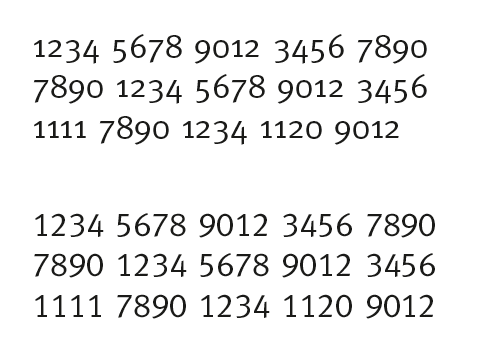
Corporate Design: Zahlen strukturieren
Ich befasse mich gerade mit einem unserer Lieblingsthemen: dem Strukturieren von Zahlen auf Briefbögen und Visitenkarten. Zum einen ist die Sache mit der Ergänzung von IBAN und BIC ja nicht gerade leichter geworden, zum anderen gibt es schriftspezifische Dinge, über die ich gerade bei der Gestaltung stolpere.
Im konkreten Fall arbeite ich mit der Meta und habe dabei für verschiedene Drucksachen die Mediävalziffern in Gebrauch.
Bei Briefbogen und Visitenkarten, die jetzt neu gesetzt werden sollen, tue ich mich damit aber schwer, weil die langen Zahlenreihen in den Bankverbindungen (es sind tatsächlich mehrere, was die Sache nicht gerade leichter macht) einen unruhigen Eindruck erzeugen und schwer zu erfassen sind – speziell dann, wenn die Zahlen ungegliedert gesetzt werden. Meine Präferenz ist daher im Moment, für die Adressblöcke komplett auf normale oder Tabellenziffern zu setzen und darüber hinaus die IBAN-Zahlenreihen in Vierergruppen zu gliedern.
Meine Frage an Euch: Wie geht Ihr mit Mediävalziffern in Adressblöcken um? Schätzt Ihr sie wegen ihrer visuellen Anpassungsfähigkeit oder fallen sie gerade deswegen für Euch sowieso raus?
Meistens tanzen sie mir dann doch zu stark ... und die "Korrektur" des Kunden, dass "alle Zahlen verrutscht sind" kommt da garantiert ...
Somit habe ich es aufgegeben, Mediäval-Ziffern für solche Sachen einsetzen zu wollen, und setze pragmatisch Versalziffern, aber ich versuche sie besser zu integrieren:
• In den seltenen Fällen dass eine Schrift Petit-Caps und dann auch noch Petit-Caps-Ziffern besitzt ... bestens!
• Alternativ kommen wenn verfügbar Kapitälchenziffern zum Einsatz
• Wenn beides nicht da ist, und die Versalziffern zu groß wirken (VERSALSCHREIBWEISE) dann versuche ich sie 1-2pt zu verkleinern und ggf. mit der nächsten Strichstärke auszugleichen. Das ist dann Handarbeit ...
• Wenn die Zeilenabstände dann noch ungleich wirken, weil andere Zeilen in Minuskeln gesetzt sind, gleiche ich diese manuell aus.
• wenn Diktengleichheit nicht erforderlich ist (meistens nicht) verwende auch keine Tabellenziffern, oder lasse sie mittels Indesign-"optisch" ausgleichen und justiere dann noch nach.
Ich würde das genau so machen wie du beschrieben hast: Mediävalziffern im Fließtext, Tabellenziffern für die Adressblöcke. Tabellenziffern eignen sich gerade bei mehrzeiligen Blöcken …
nur eine terminologische anmerkung: mediävalziffern und tabellenziffern sind keine begrifflichen gegensätze. man könnte deine empfehlung dahingehend missverstehen. es gibt allerdings in vielen schriftarten auch mediävale tabellenziffern und natürlich proportional zugerichtete versalziffern. falls jemand auf dieses thema stößt und noch mal wissen will, wie es ist:
zifferngestaltung:
mediävalziffern: teilweise hängende ziffern
versalziffern: nur ›stehende‹ ziffern
ziffernzurichtung:
proportional zugerichtete ziffern: jede ziffer hat ihre eigene, ›natürliche‹ breite
tabellarisch zugerichtete ziffern: alle ziffern haben dieselbe breite
wenn deine version der meta auch dicktengleiche minuskelziffern hat würde ich auf jeden fall probieren ob’s gut aussieht. aber sebastians kunden-erfahrung kennen wir natürlich alle.
Ich denke, ich zeige dem Kunden beide Varianten, da sie beide etwas für sich haben. Der Kunde ist in Gestaltungsfragen versiert, daher – denke ich – kann ich ihm die Entscheidung zumuten.  ;-)
Ich habe letzte Woche im Rahmen eines Uniseminars am Rand meines Vortrags verschiedene Schriften gezeigt, einfach um die Studierenden dafür zu sensibilisieren, dass es mehr gibt als das, was auf ihren Computern vorinstalliert ist. Es lief alles wie erwartet, bis zu einer Tafel mit Beispielen von Serifenschriften, darunter Times New Roman (quasi als Ausgangsbasis, da sie für studentische Arbeiten immer noch oft vorgegeben ist) und dann verschiedene Schriften, die ich so herum zu liegen hatte, z.B. eine Garamond, Vollkorn und die neue Kefa II. Ohne dass ich danach gefragt hätte, gab es mehrere spontane Zwischenrufe:
Student 1: “The first one [TNR] is the best!”
S2: “Yeah, it’s the prettiest.”
Ich: “Why do you prefer this typeface?”
S3: “It doesn’t have those crazy numbers!”
S4: “Yeah, those are weird!”
Darauf gab es zustimmendes Gemurmel und die ganze Klasse hat mich mit freudiger Zuversicht angestrahlt, weil sich alle sicher waren, »richtig« getippt zu haben. Beim Gestalten der Tafel war mir gar nicht aufgefallen, dass das TNR-Beispiel das einzige mit Versalziffern war. Alle anderen Beispiele hatten Mediävalziffern.
Außerdem sind Mediävalziffern je nach Schriftart ganz anders ausgeprägt. Bei manchen Schriften sind die Ober- und Unterlängen im Vergleich zum Rest besonders groß, bei anderen Schriften besonders klein. Ist letzteres der Fall, kann man die Ziffern viel eher auch wie Versalziffern benutzen. Kommt immer drauf an. Und wann man zwei Ziffernarten in einer Drucksache oder einem Corporate Design mischt, hängt ja auch wieder von verschiedensten Faktoren ab. Auch da wären Generalisierungen fehl am Platze.